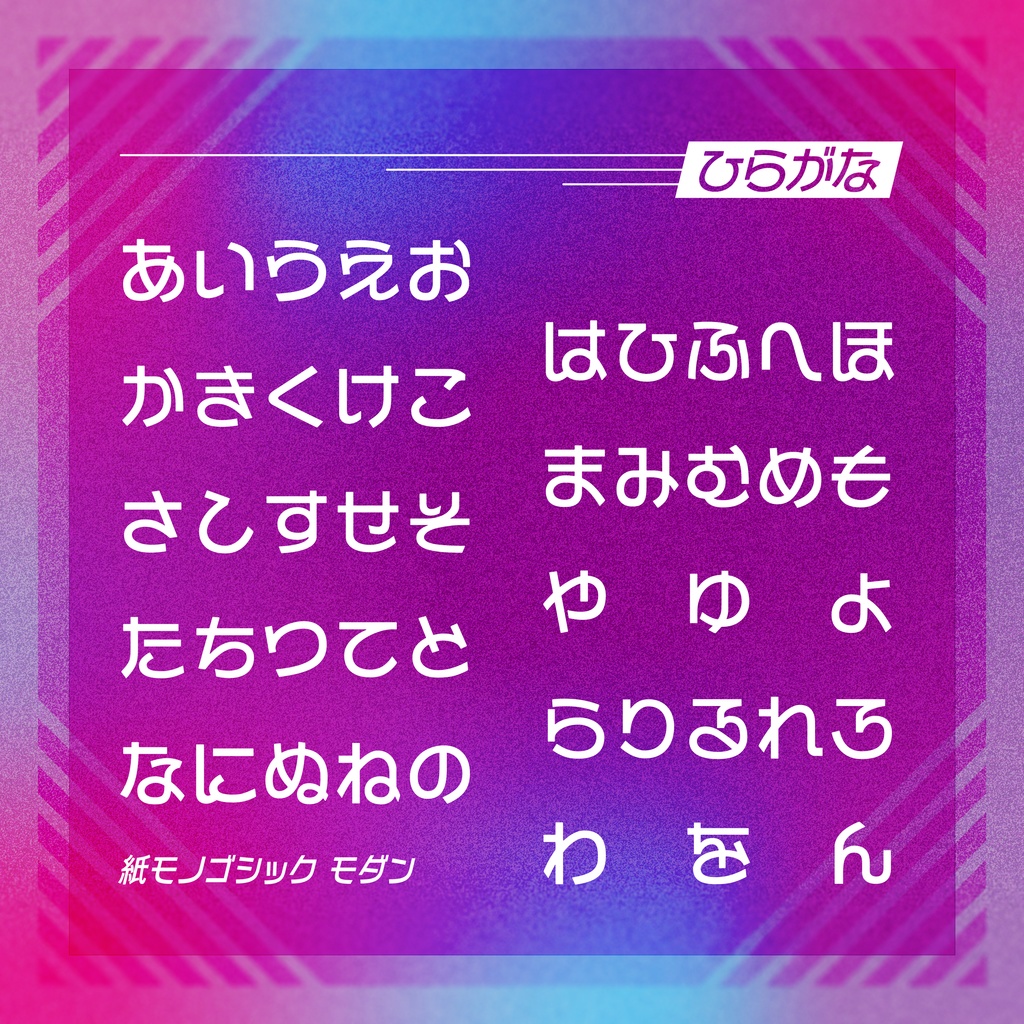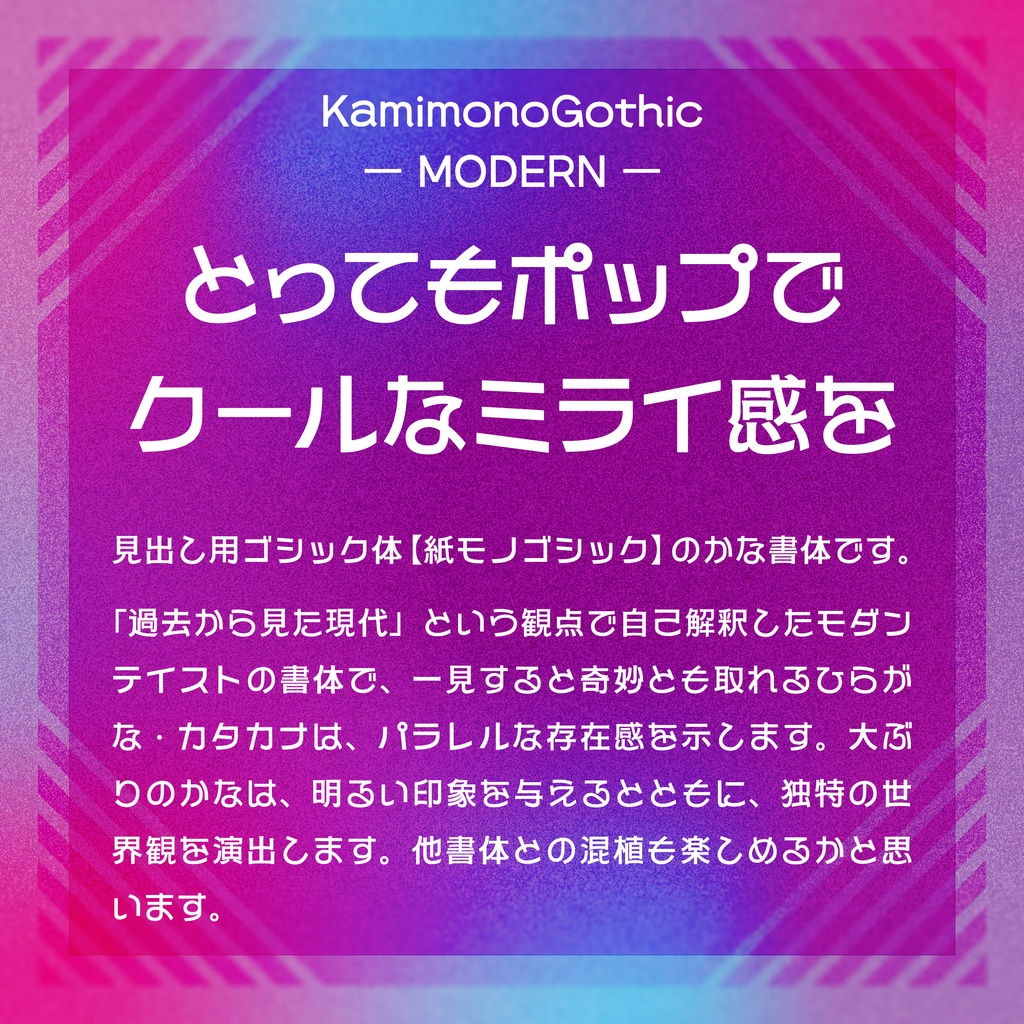
【フリーフォント】紙モノゴシック モダン
【このフォントについて】 見出し用ゴシック体〈紙モノゴシック〉のかな書体です。漢字・記号などは〈紙モノゴシック〉と同一のものとなります。 「過去から見た現代」という観点で自己解釈したモダンテイストの書体で、一見すると奇妙とも取れるひらがな・カタカナは、パラレルな存在感を示します。大ぶりのかなは、明るい印象を与えるとともに、独特の世界観を演出します。他書体との混植も楽しめるかと思います。 ※投げ銭版の収録内容は無料版と全く同じです。もし気に入っていただけたらよろしくお願いします。フォント制作の励みになります。 無償利用・商用利用問わず、自由にご使用いただけます。 印刷物のみならず、ゲームやWebなど何にでもご活用ください。 当フォントを利用した制作物などを、X(旧Twitter)で報告していただけると、とても励みになります。 不具合の修正や新しいグリフの追加が行われていますので、最新のバージョンをご確認ください。 【すずみばと書林】 《もじピジョン》と《Suzumi Designs》による2人組のフォント制作ユニットです。 共同制作のフォントを配布・販売しています。 「書林」は本来「多くの書籍が集まるところ」という意味ですが、ここでは「多くの書体が集まるところ」という意味を込めて名付けました。 新作フォントの公開やバージョンの更新情報はそれぞれのX(旧Twitter)でアナウンスしています。当フォントダウンロードの折には、フォローしていただけると幸いです。 《もじピジョン/X(旧Twitter)》https://twitter.com/Moji_Pigeon 《Suzumi Designs/X(旧Twitter)》https://twitter.com/Suzumi_Designs 【収録文字】 ひらがな・カタカナ・英数字・一部約物・漢字(教育漢字+α) (最新ver.1.0) 【更新履歴】 ver.1.0 リリース 【利用規約】 ・利用条件 1)当フォントを入手・使用したことによるいかなる損害も使用者自身が責任を負うものとします。 2)無償利用・商用利用ともにご自由にお使いいただけます。 3)クレジットの表記は不要です。 4)当フォントの二次配布は可能ですが、その際はこのtxtファイルを添付するようにしてください。なお、二次配布の際は一言いただけると幸いです。 5)当フォントを加工・変形してご利用いただけます。 6)ゲームやWebサイトに埋め込んでご利用いただけます。 ・禁止事項 1)当フォントを公序良俗に反する目的で使用することはできません。 2)当フォントを利用したロゴマーク等の商標登録はできません。 3)当フォントデータ・プログラムを、無断で改変したものを配布することはできません。 4)当フォントの制作者を騙った発言等はできません。